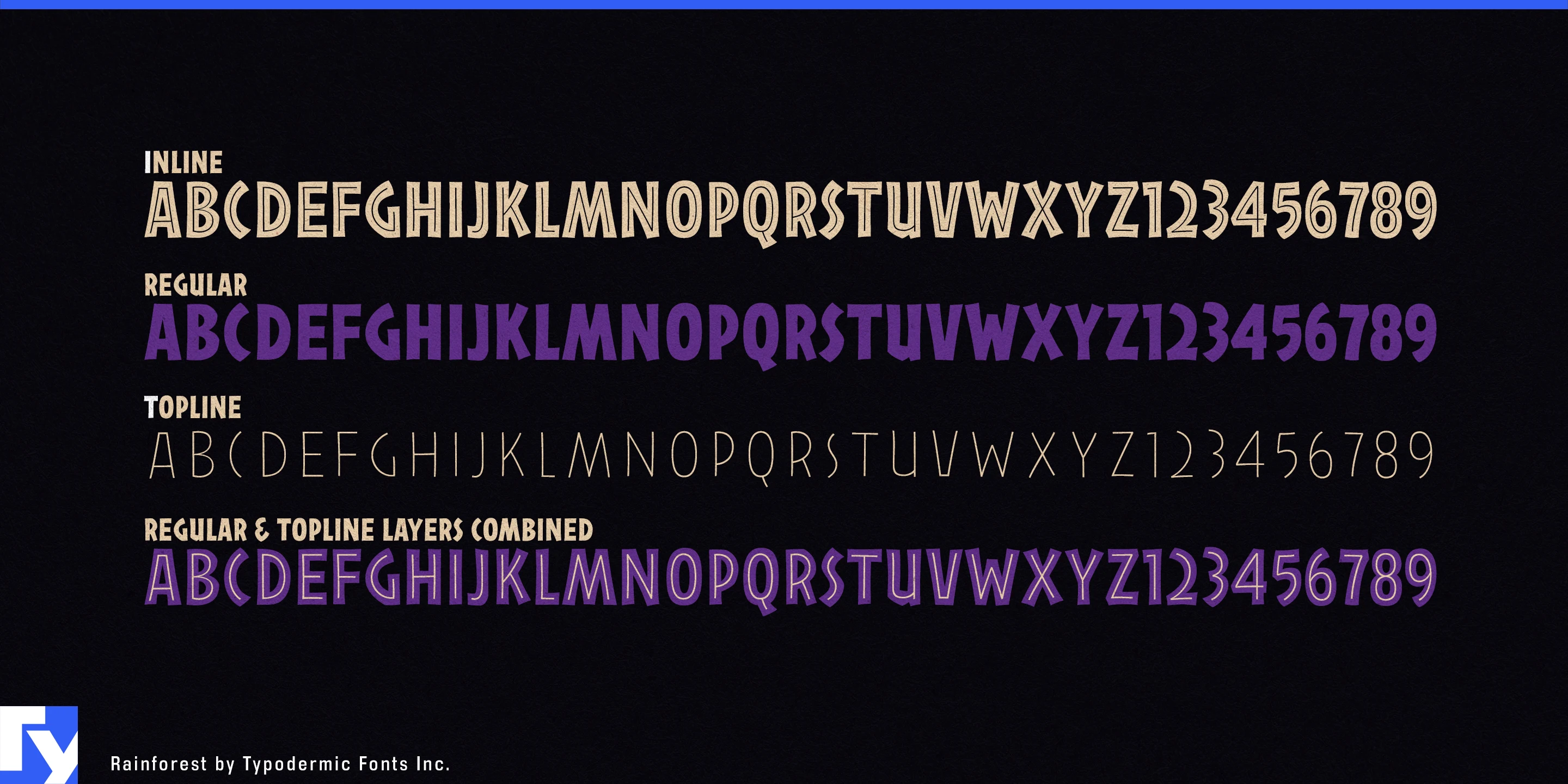
Rainforest
Rainforestは、鈍く不規則に切られた形と、短い語を看板、パッケージ、ポスターの主役にできる縦方向の存在感を持つ、幅狭のスモールキャップ書体です。Regular、Inline、Toplineはレイヤー状に組み合わせられます。基礎のプロポーションを変えずに、強い前景色とアクセント色を組み合わせる複数の方法を与えます。
カリブ海のリゾートや島のレジャー事業は自然な用途です。ビーチクラブ、水辺のホテル、リゾートのプール、カタマランでの遊覧、シュノーケリングの事業者、ダイビングセンター、マリーナのイベント、熱帯の観光地のキャンペーンでは、会場名、遊覧の見出し、プールのプログラム、レストランの分類、グッズ、季節のグラフィック、イベント名にRainforestを使えます。アクア、コーラル、マンゴー、ライム、バイオレットなど鮮やかな色の組み合わせなら、偽の部族風の模様や時代遅れのジャングルの戯画に頼らず、陽光の下のレジャーへ文字を寄せられます。
食品や飲料にもその活力を広げられます。唐辛子のソース、ジャーク風のマリネ、スパイスミックス、プランテンチップス、熱帯果実の飲料、冷たいデザート、魚介料理の店、現代的なカリブ海料理のブランドなどです。Rainforestは製品名、ソースの種類、パウチの正面、瓶のラベル、持ち帰り用のグラフィック、市場の表示を担えます。幅狭のプロポーションはイラストや補助情報の余地を残し、レイヤー式のスタイルは味や種類に十分な存在感を与えます。
Rainforestの先史時代らしい面も同じように役立ちます。自然史博物館、恐竜公園、巡回する化石展、古生物学のギャラリー、没入型のアトラクション、家族向け科学館では、展示タイトル、種ごとの区域、アトラクション名、来場者向けのキャンペーン、教育キット、記念グッズに使えます。恐竜フィギュアのシリーズ、化石発掘キット、STEMの活動セット、博物館の売店商品も、包装と店頭展示へ同じ視覚言語を広げられます。
熱帯の水族館、サンゴ礁の展示、ウミガメの施設、植物園、熱帯植物の温室、樹冠を歩く遊歩道、熱帯雨林の来訪者施設も自然な環境です。展示の見出し、来場者向けのプログラム、散策路の区間、グッズ、家族向け活動資料では、Rainforestの不規則で幅狭の形を生かしながら、InlineとToplineで密度の高い写真やイラストに対して色と分離を加えられます。
ウォーターパーク、リゾートの子ども向けクラブ、水遊びエリア、ミニゴルフなどの家族向けレジャー事業でも、同じレイヤー構造で区域、活動、季節のプログラムを区別できます。Rainforestはラグーン、サンゴ礁の水槽、熱帯の葉、化石層、巨大な爬虫類のどれにもなじみます。幅狭の量感、不規則な形、重ねた色が、それぞれの世界へ強いディスプレイ文字を与えます。